モリサワによる好きな言葉&デザイン&フォントで自分にぴったりのオリジナルデジタルスタンプが作れる大阪・関西万博記念!サイト「フォント de スタンプ」がオープン
モリサワは、2025年日本国際博覧会(以下、大阪・関西万博)モチーフのデザインも選べるオリジナルスタンプ作成サイト「フォント de スタンプ」を8月6日(水)より公開した。
本サイトでは、モリサワのフォントを使って、好きな名前や言葉を入力し、デジタルスタンプ(スタンプ形式のデジタル画像)を作成できる。
電子印鑑をはじめ、SNSのアイコンや写真に加工したり、自分自身でLINEスタンプにしたり、推し活素材として活用したりするなど、自由にアレンジして利用することが可能。
スタンプのフレームデザインは合計9種類で、期間限定で大阪・関西万博モチーフのデザインも選択可能となっている。
使えるフォントは12種類で、モリサワのフォントの中でも定番のフォントや人気のフォントを採用。
自分の言葉で自分にぴったりのオリジナルのデジタルスタンプを作成でき、フォントを変えると言葉の印象が変わる楽しさを体験することができる。
本サイトの公開を記念して、モリサワ EXPO2025推進室 PRストラテジスト・野口季果子氏に特別インタビューが実施され、企画背景や、工夫したポイント、活用方法など語られた。
また、作成したデジタルスタンプが、本物のハンコになって届くプレゼントキャンペーン「万博記念!フォントが選べるオリジナルハンコプレゼント」も実施。
ハンコのハンドル部分は、大阪・関西万博記念としてミャクミャクのデザインとなっており、ここでしか手に入らないハンコとなる。
オリジナルスタンプ作成サイト「フォント de スタンプ」についてモリサワは、「大阪・関西万博PRブロンズパートナー」として協賛。
モリサワのフォントを使って、好きな名前や言葉を入力し、デジタルスタンプ(スタンプ形式のデジタル画像)を作成できる。
電子印鑑をはじめ、SNSのアイコンや写真に加工したり、自分自身でLINEスタンプにしたり、推し活素材として活用したりするなど、自由にアレンジして利用することも可能。
また、自分で作成したスタンプをサイト上のギャラリーに公開することもできる。
他の利用者が作成してギャラリーに公開しているスタンプも閲覧可能で、スタンプが気に入ったらダウンロードすることも可能。
フレームデザインとフォントについて
スタンプのフレームデザインは合計9種類、使えるフォントは12種類で、デザインの組み合わせは全部で108通り。
フレームは、ここでしか手に入らない大阪・関西万博モチーフのものも用意。8月6日(水)~10月13日(月)の期間限定で選択できる。
フォントは、大阪・関西万博の会場サインなどにも採用されている「UD新ゴ」や、うちわ文字としてよく使われ、実はWebサイトの書体別ページでは圧倒的に閲覧数が多い筆書体「勘亭流」など、モリサワのフォントの中でも定番のフォントや人気の高いものを採用。
一般的な制作ツールの場合、フォントを選んでから文字を入力する形が基本だが、本サイトではフォントを指定せずに文字を入力し、入力した文字が12種類のフォントでプレビュー表示されるため、見比べてから選ぶことが可能。
また、フォントの種類が似たものが近くに表示されるため、例えば同じ「ゴシック体」同士の見比べがしやすい仕様になっている。
モリサワと大阪・関西万博について
大阪に本社のあるモリサワは、パソコンやスマートフォンなどで使用される「フォント」を開発・販売しているメーカー。
「大阪・関西万博PRブロンズパートナー」として協賛、会場サインやアプリで使用される各種フォントを提供しているほか、パビリオンなどでも各種フォントが採用されている。
会場内で使用されるUD(ユニバーサルデザイン)フォントは、EXPO2025に訪れる多くの方々に「読みやすさ」を伝えています。モリサワは文字の力で、大阪・関西万博を応援している。
※大阪ヘルスケアパビリオンにもサポーターとして協賛しフォントを提供している。
デジタルスタンプ作成の流れ
(1)サイト上の簡単な質問に回答すると、デジタルスタンプ作成ページに進める。
(2)9種類の中から、好きなデザインの台紙(フレーム)を1つ選ぶ。
プレビュー後に変更も可能。
(3)スタンプに入れたい文字を入力。
(例:「ありがとう」「さとし」「推し最高!」など自由に入力可能)
・1~3行(フレームによって異なる)まで文字を入力することが可能。
・各行で指定されている文字数以内で入力。
※不適切な表現が含まれている場合、スタンプを作成できないことがある。
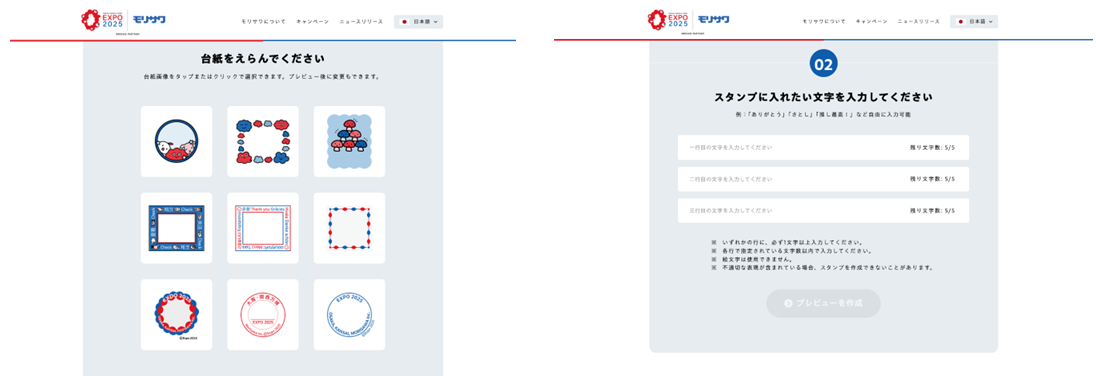
(4)プレビューから気に入ったものをダウンロード。
12種類のフォントで表示される。
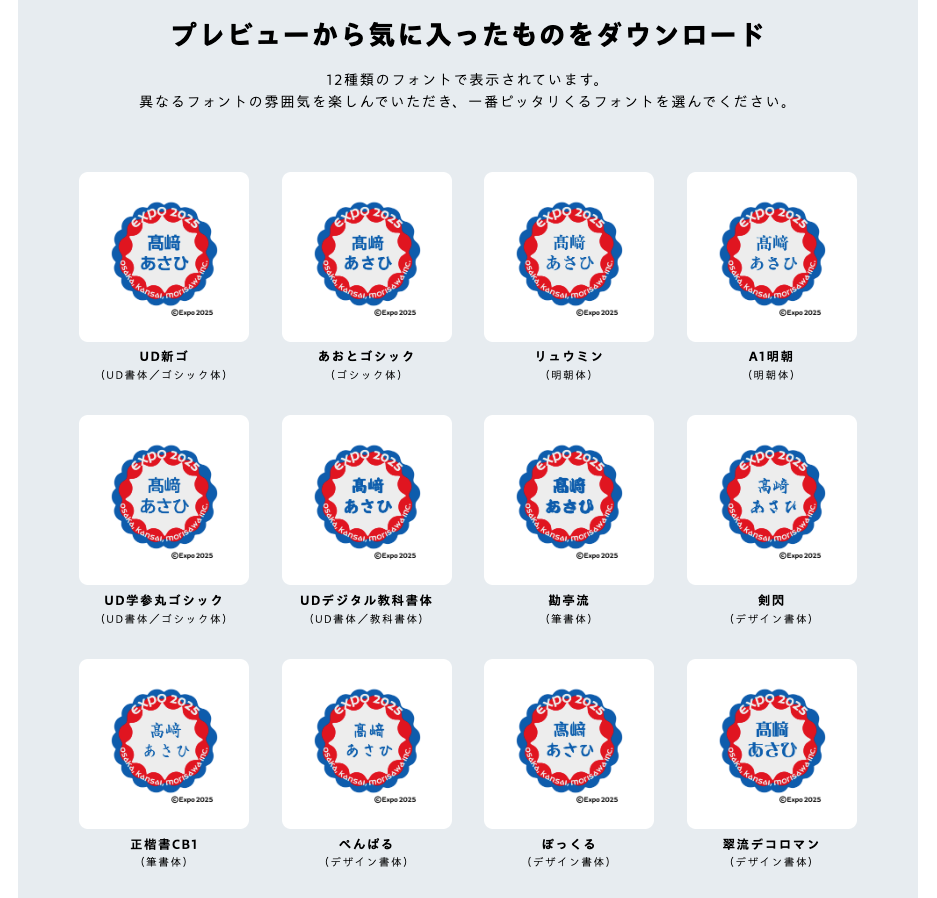
台紙(フレーム)
▼大阪・関西万博モチーフ※8月6日(水)~10月13日(月)の期間限定で選択可能
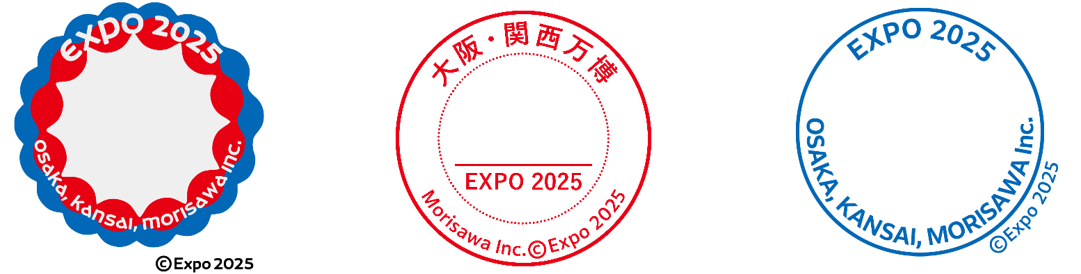
▼その他
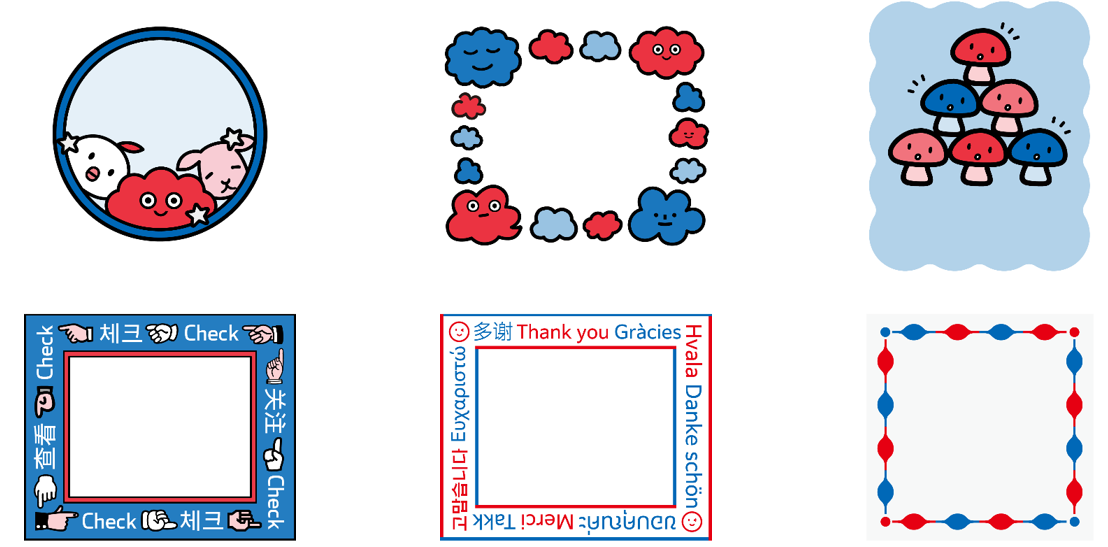
モリサワ EXPO2025推進室 PRストラテジスト・野口季果子氏特別インタビュー
本サイトの公開を記念して、株式会社モリサワ EXPO2025推進室 PRストラテジスト・野口季果子に特別インタビューを実施しました。オリジナルスタンプ作成サイト「フォント de スタンプ」の企画背景や、工夫したポイント、活用方法などについて聞きました。
――オリジナルスタンプ作成サイト「フォント de スタンプ」の企画・実施背景や、込めた思いについて教えてください。
大阪・関西万博PRブロンズパートナーとして協賛させていただいているため、まずは大阪・関西万博を一緒に盛り上げたいと考えました。また、会場に足を運べない遠方の方にも万博の記念になるようなものをお届けしたいということでオンラインの企画にしました。幅広い方がスマートフォンを持ち、小学校もICT教育が進んでいるので、日常的にフォントを使っている方は増えていますが、フォントを意識して選んで使われている方は多くないかもしれません。この機会に、フォントによる印象の違いなどを体験いただけますと幸いです。
――実施に至るまで大変だったことや、工夫したことはありますか?
皆さんが普段使われている制作ツールの場合、フォントを選んでから文字を入力することが一般的かと思います。ただ、この場合、フォント名だけではどんな文字かをイメージできず、選びにくい方も多いのではないでしょうか。今回は、普段フォントを選ぶことに不慣れな方にも楽しんでいただきやすいよう、フォントを指定せずに文字を入力してもらい、12種類のフォントのプレビューを表示させ、フォントによる印象の違いを体感していただきながら1つを選択してもらう形にしました。自分の伝えたい言葉にぴったりのフォントを見比べて選んでいただくことができます。
――大阪・関西万博とのコラボデザインを作成した理由・狙いは何でしょうか?
大阪・関西万博の記念になるものを、自分の名前や届けたいメッセージなど、好きな言葉で作れる、という体験をしていただくことが、今だけの忘れられない体験になるのではと考えました。
――どんなシーンで使ってほしいですか?また意外な活用方法があれば教えてください。
――どんな方に使ってほしいですか?
お子様から大人まで、幅広い方に楽しんでいただきたいです。普段、制作ツールを使い慣れていない方でも簡単にオリジナルのスタンプデータが作れるので、試していただきたいです。作ったスタンプはギャラリーに公開して、他の方に楽しんでいただくこともできます。
――モリサワの今後の展望を教えてください。
スタンプを作成いただく際に、簡単な質問にお答えいただく設計にしています。どのような方々がどのフォントを選んでいただいたか、などの情報は今後のフォント開発やフォントサービスの展開に活かしていければと考えています。
オリジナルスタンプ作成サイト「フォント de スタンプ」で作成したデジタルスタンプが、本物のハンコになって届くプレゼントキャンペーン「万博記念!フォントが選べるオリジナルハンコプレゼント」を実施。
自分の名前や好きな言葉、推しワード、オリジナルのメッセージなど、選んだ言葉とフォントがハンコになる。
ハンコのハンドル部分は、大阪・関西万博記念としてミャクミャクのデザインとなっており、大阪・関西万博の記念品としても思い出に残るデザインとなる。